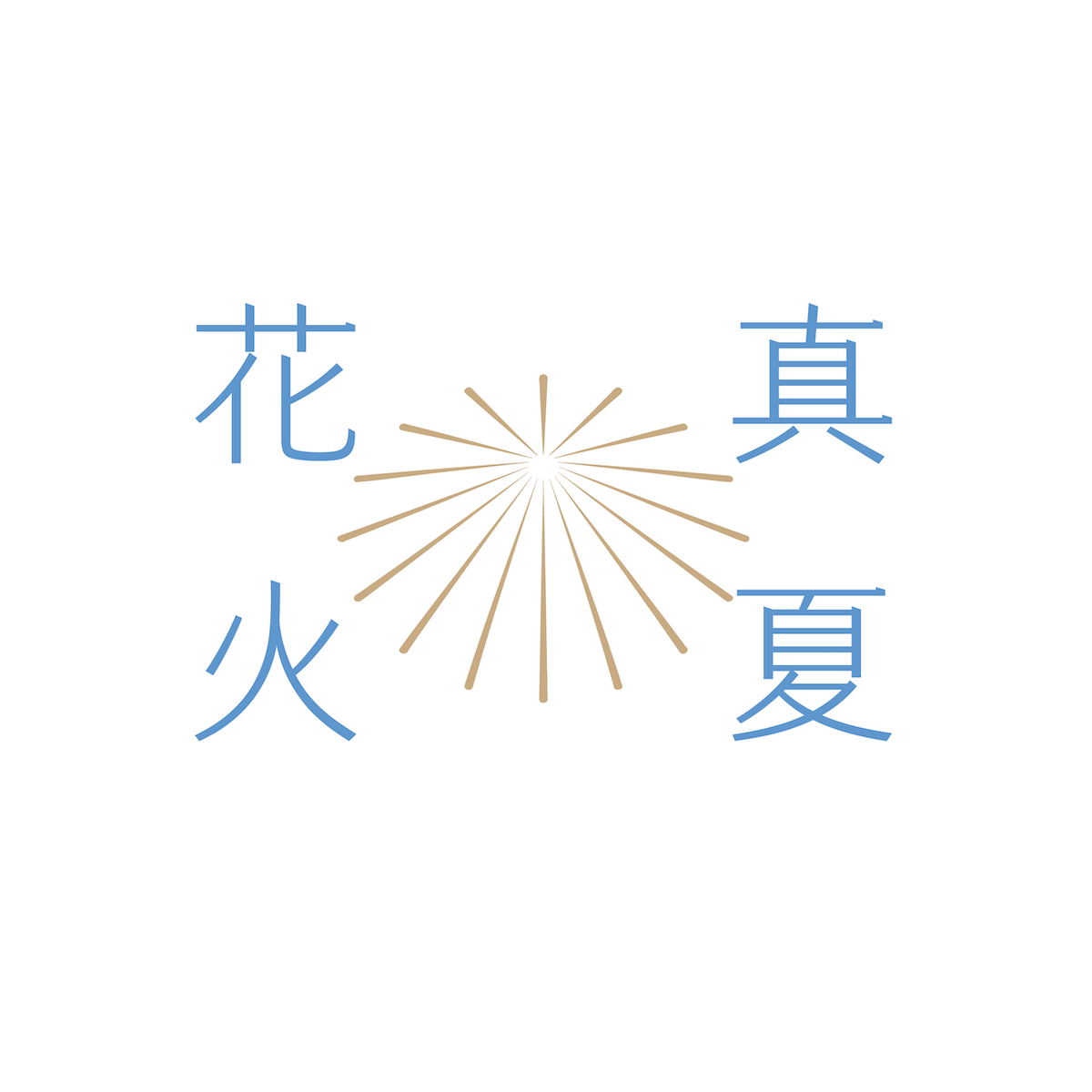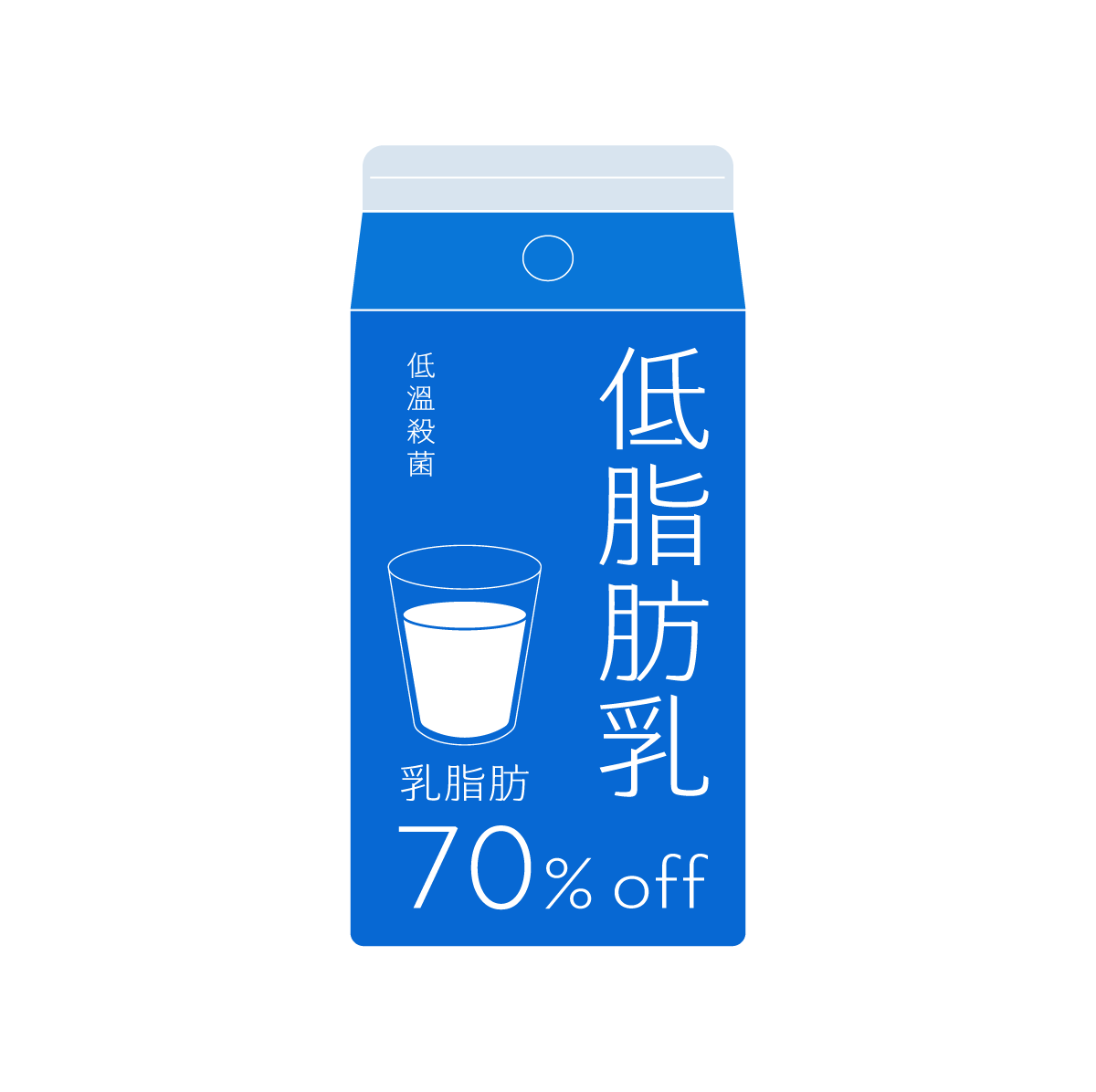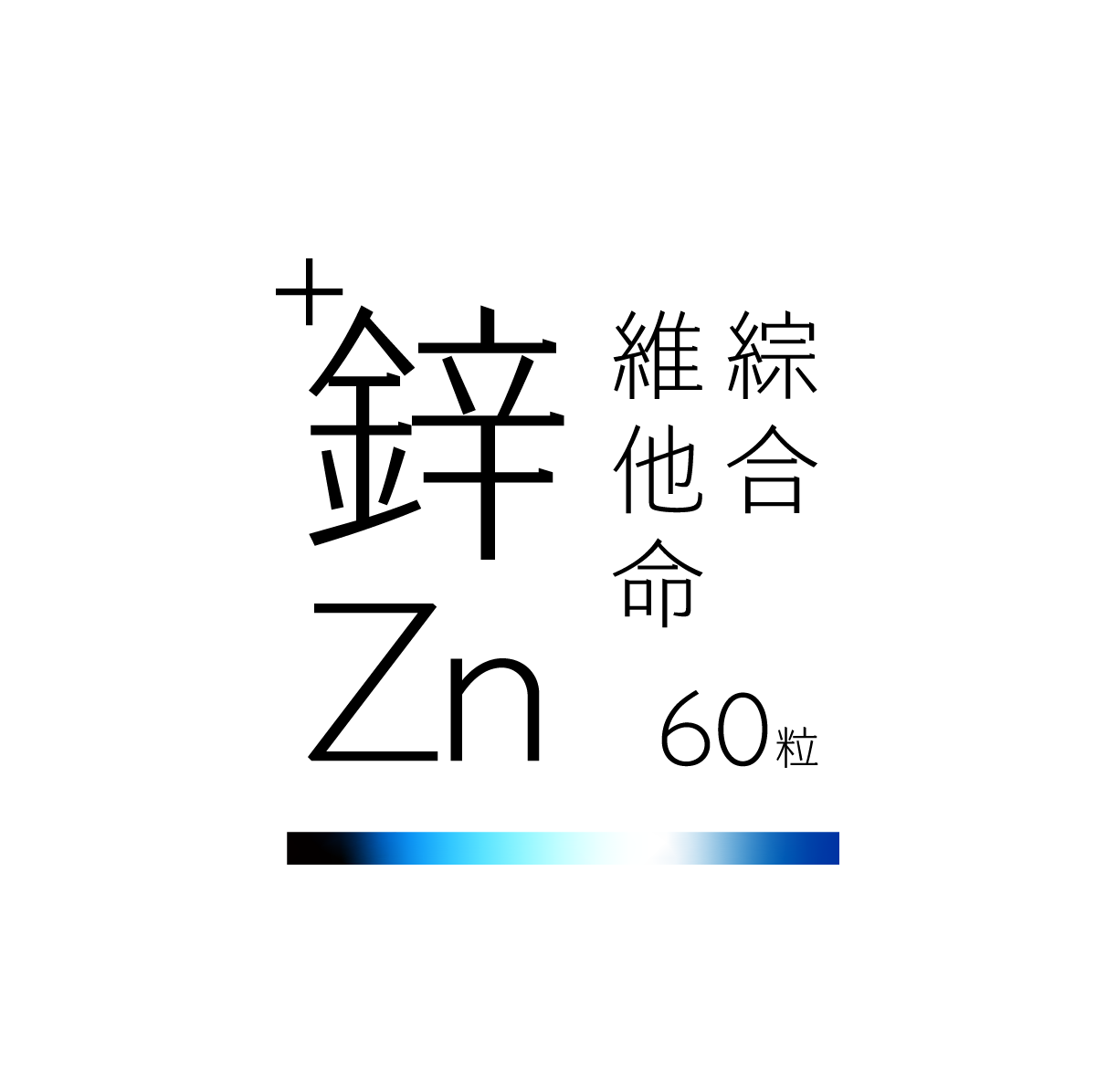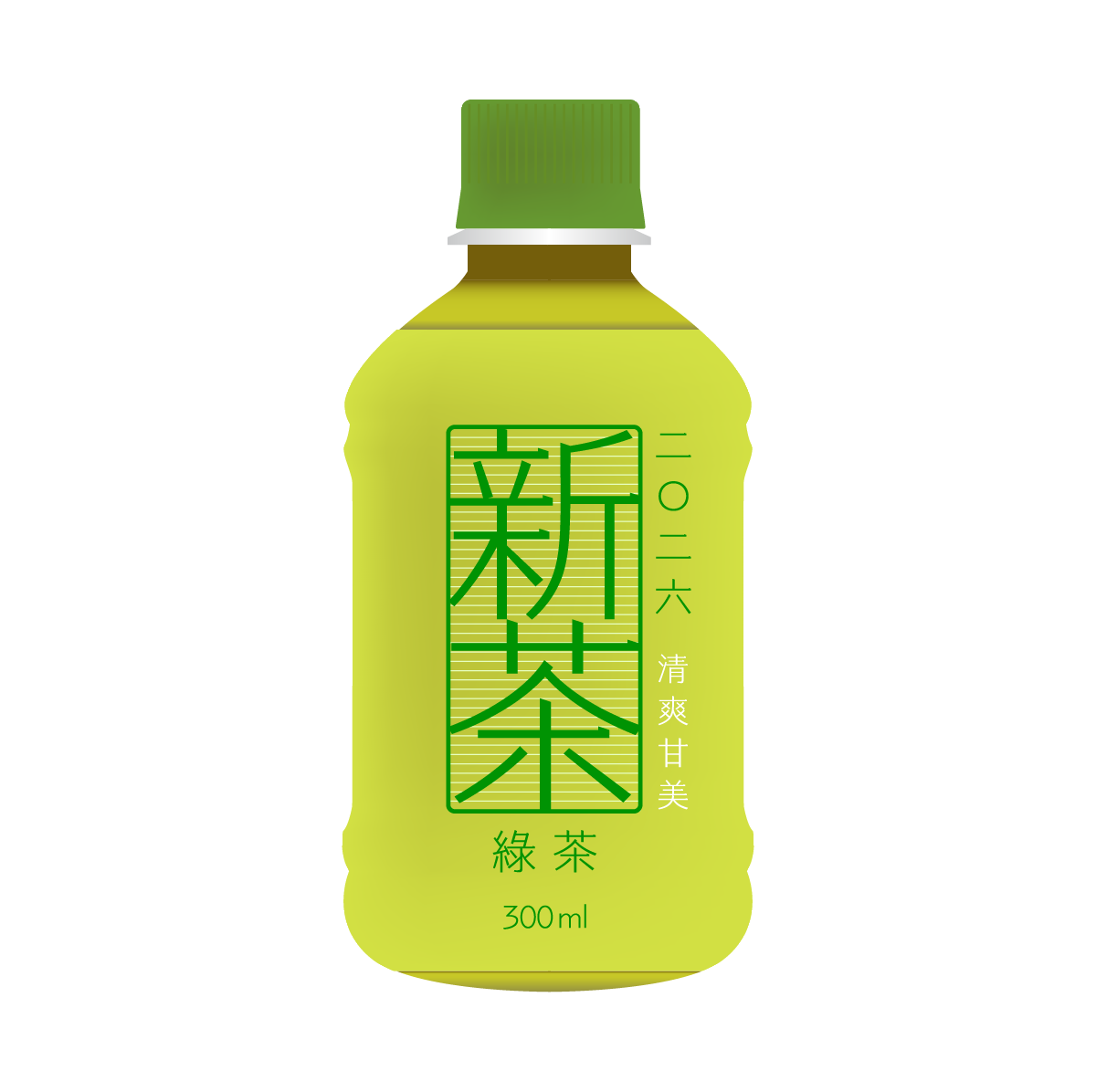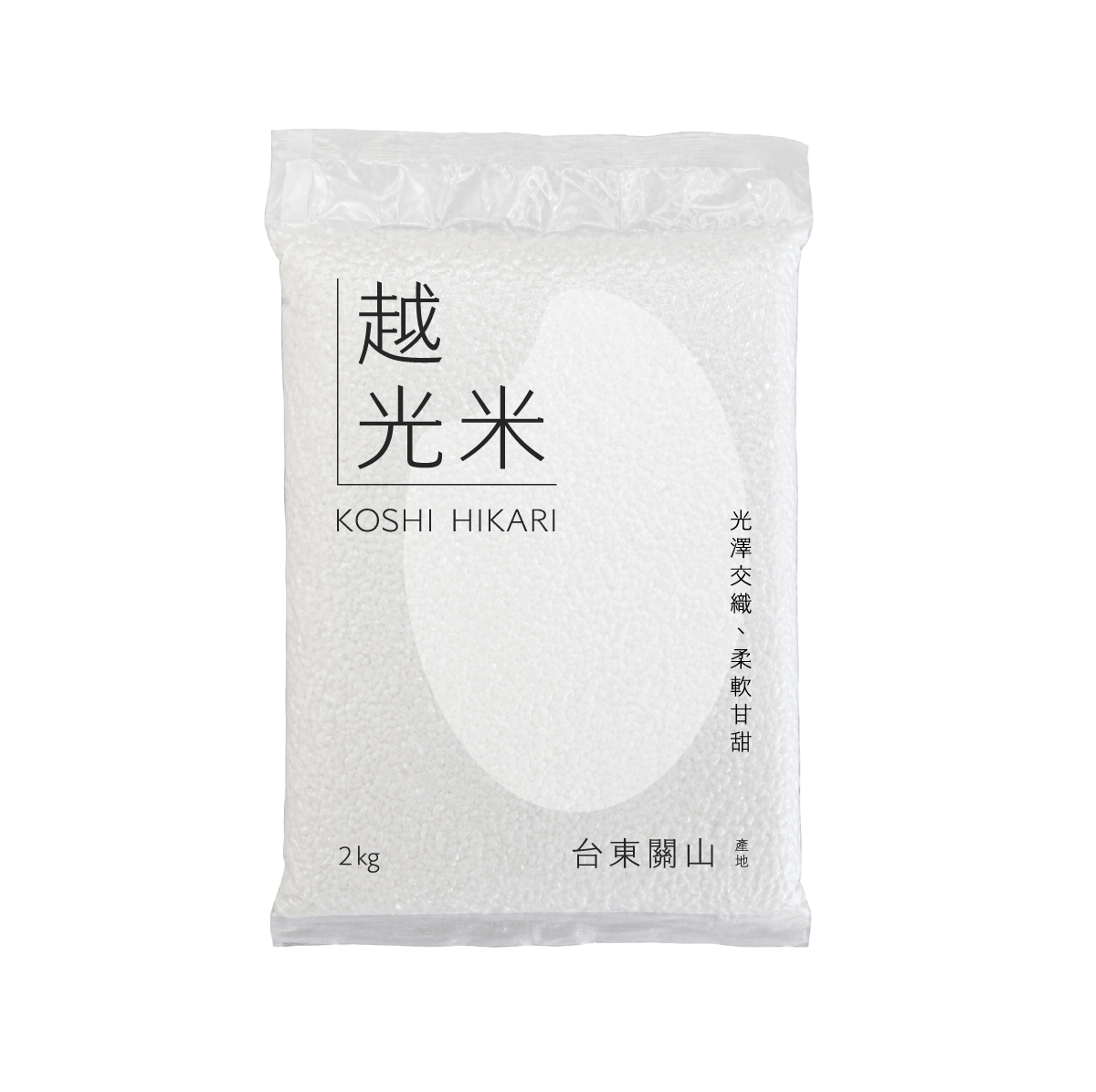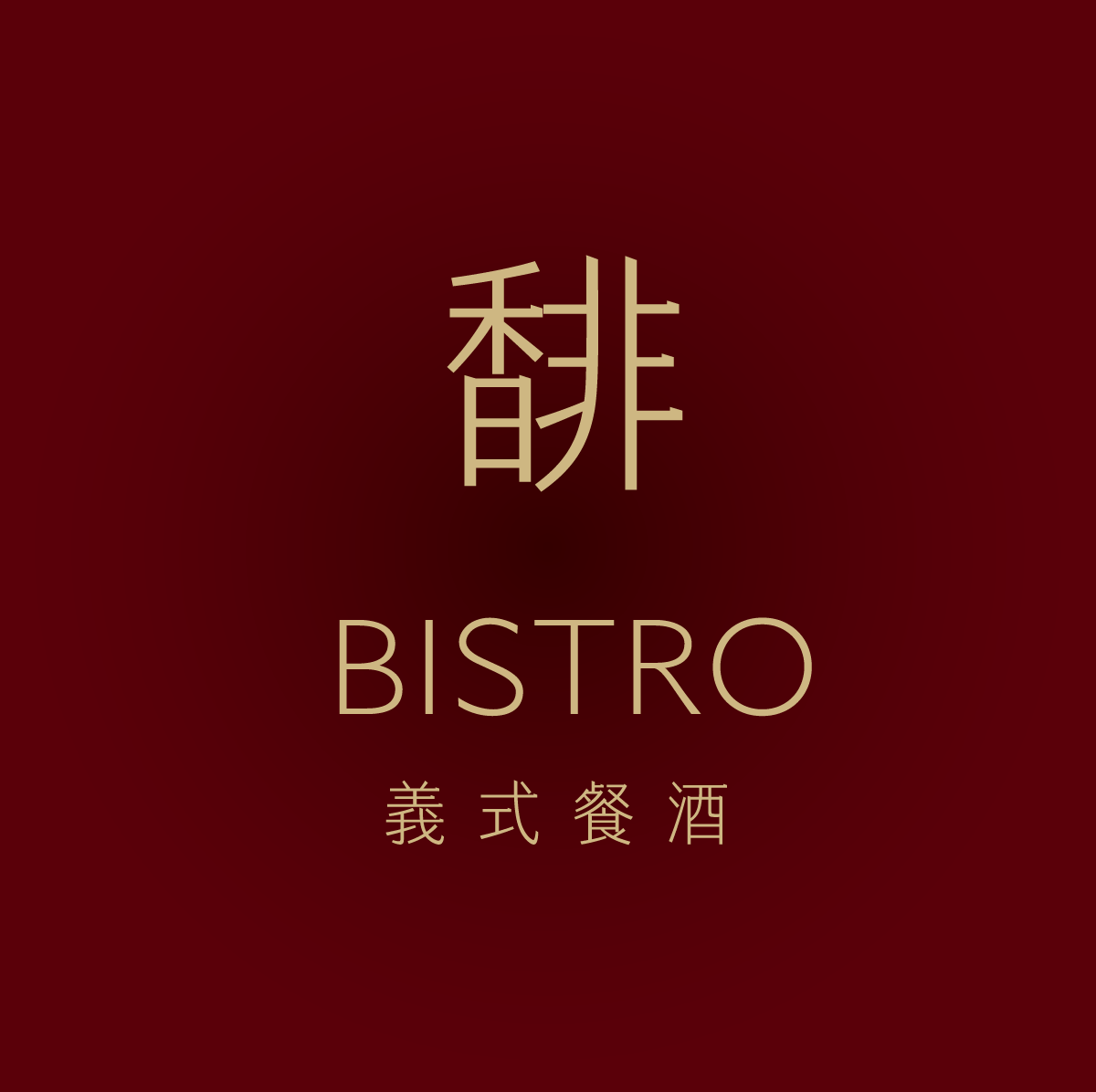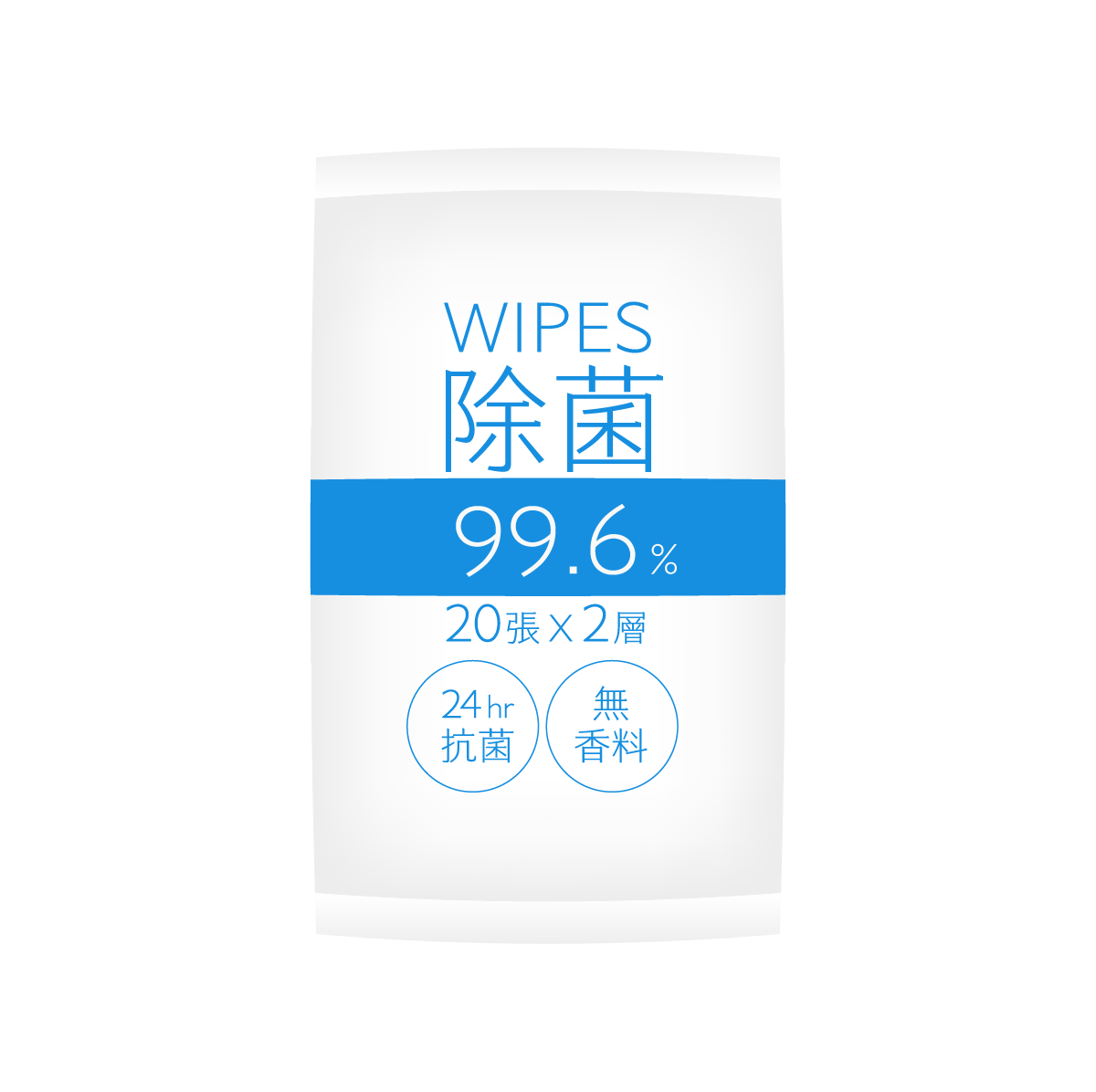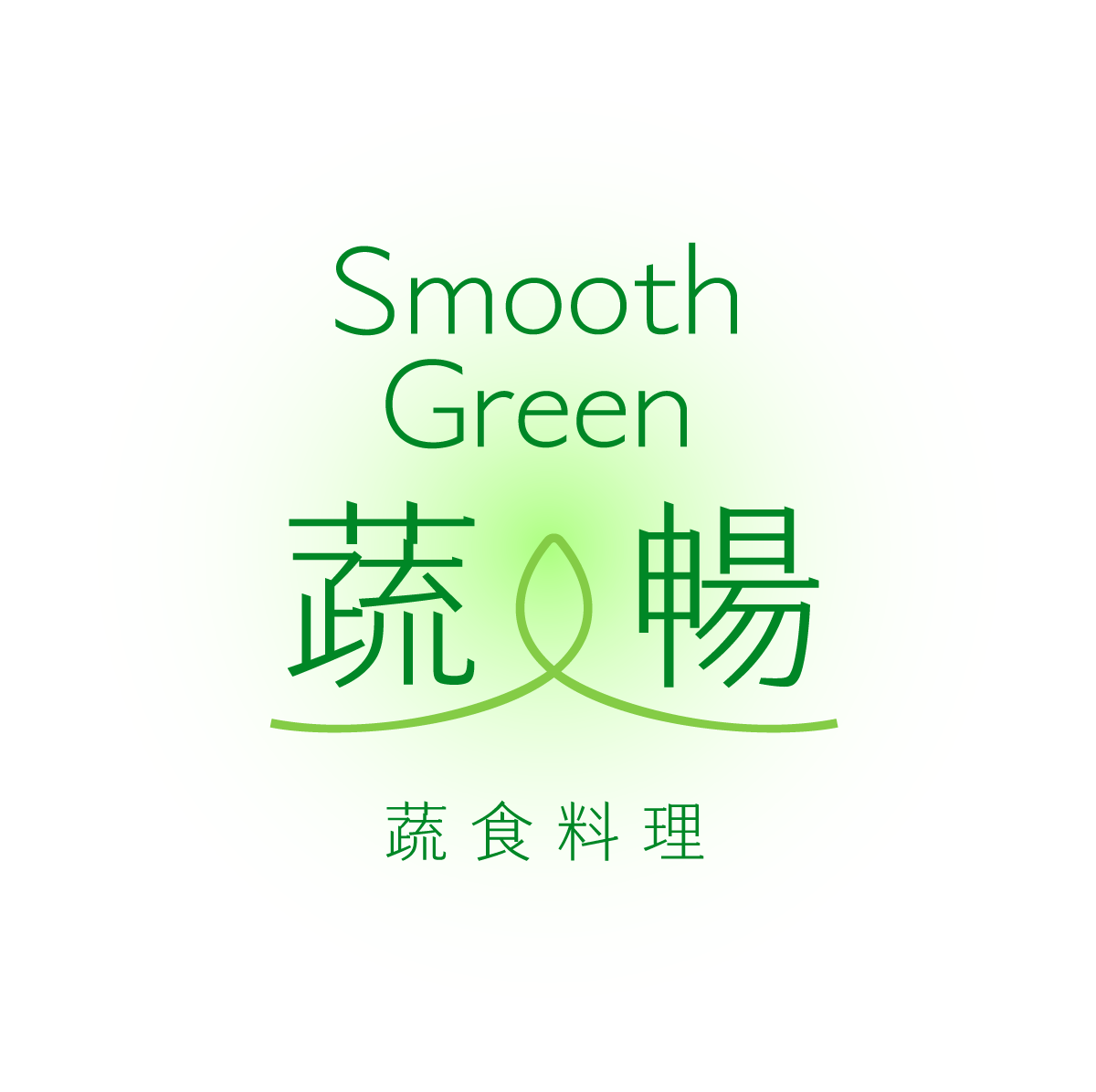
松韻 繁中版
給大標題的細字體,纖細不纖弱。松韻是風格現代、簡約清爽的字體。理性精準的架構,讓大標題應用既穩定又有存在感。
字型設計師
施博瀚
擅長品牌企劃、識別設計、標準字設計。作品曾獲金點概念設計獎年度最佳設計、DFA亞洲最具影響力設計獎等,並相繼收錄於多本設計刊物中。現為 Bohan Graphi© 設計工作室負責人、中文字型「凝書體」創作者。著有《LOGO設計研究所》一書(如何出版)。